意外と多い仮名系グリフ03「半角、組文字」
前回(濁点・半濁点つき仮名、小書きの仮名)からの応用力が試される半角と組文字の制作ポイントの紹介です。
半角仮名
横幅を50%縮小した後で調整します。特に太いウエイトでは黒味の調整が難しく感じることがあります。縦画横画の太さが自然に見えるバランス、他のグリフと黒味を合わせること、などいくつかの観点に気を配りながらちょうど良いアウトラインを探っていきます。
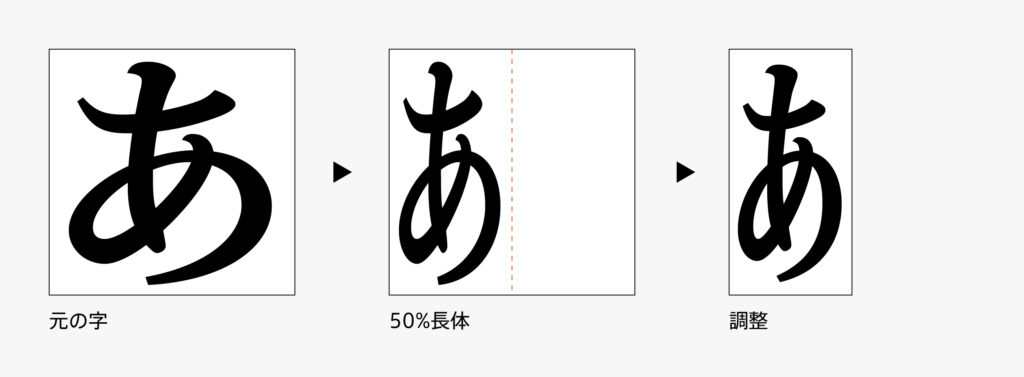
例えば長体ファミリーがあるTPスカイの場合、長体の仮名グリフも半角と同じように作っていきましたし、長体のさらに半角でかなり幅の狭いグリフまで用意しました。
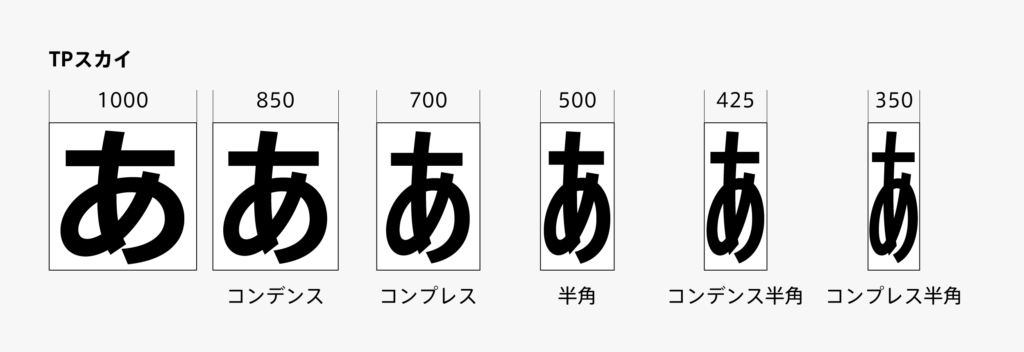
仮名の組文字
元になる仮名のデザインが決まったら「㍉㍑㌕」などの組文字も作ります。文字を縮小し組み合わせて、太さ、字幅、配置などを調整していきます。1グリフとしてのまとまり、一緒に組む文字とのバランスなどを意識しています。
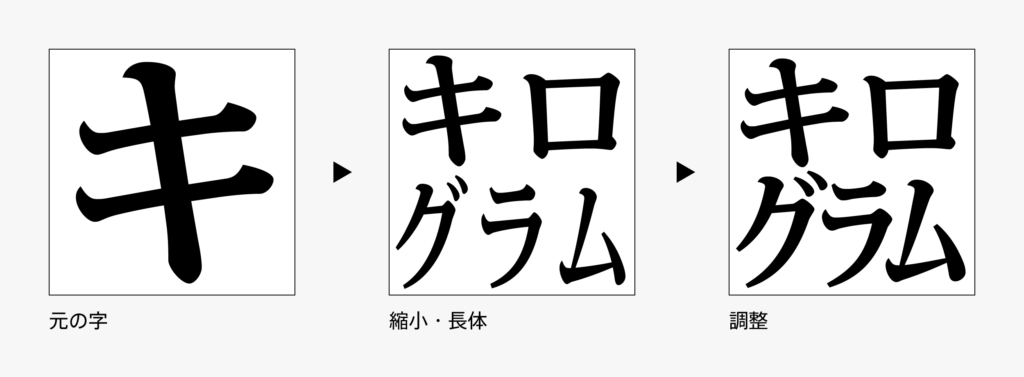
組文字にも横組用と縦組用があり、それぞれ縦の流れと横の流れを見ながら文字の配置を決めています。